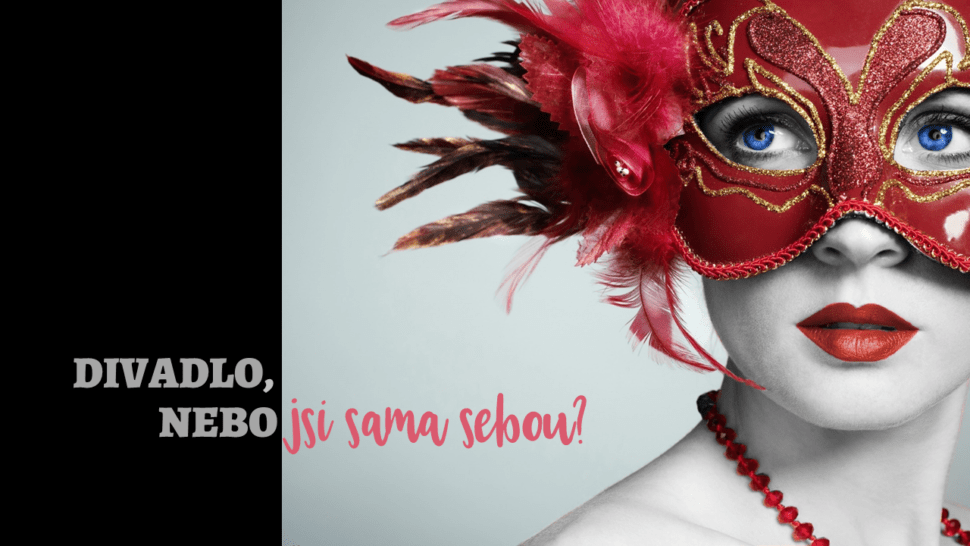
FONTY & OSOBNOST
Fonty mají stejný charakter, jako lidé.
Fonty dokonale odráží to, jací doopravdy jste.
Popíšou váš charakter, hodnoty, nastavení vůči druhým. Prozradí na vás, jestli se rádi dlouze vybavujete, nebo jdete raději přímo k věci. Jak moc vás ovlivňují emoce a jestli je vaší silnou stránkou intuice a kreativita anebo analytický přístup. Jsou vaším zrcadlem.
Pokud chcete, aby si vás klienti vybírali právě proto, že s tímto nastavením souzní a potřebujete mít dobrý pocit, že jste sami sebou v každém okamžiku, vyberete si vlastní font, který bude vaší součástí.
Kdy je načase zamyslet se nad výběrem fontu?
Máte krásný web, ale nemá vaší esenci.
Obrací se na vás klienti, které nechcete.
Potřebujete, aby byly jasně viditelné hodnoty, které jsou pro vaše podnikání zásadní.
Font je nedílnou součástí vizuální identity každého člověka a stojí za to si ho vybrat s jasným záměrem.